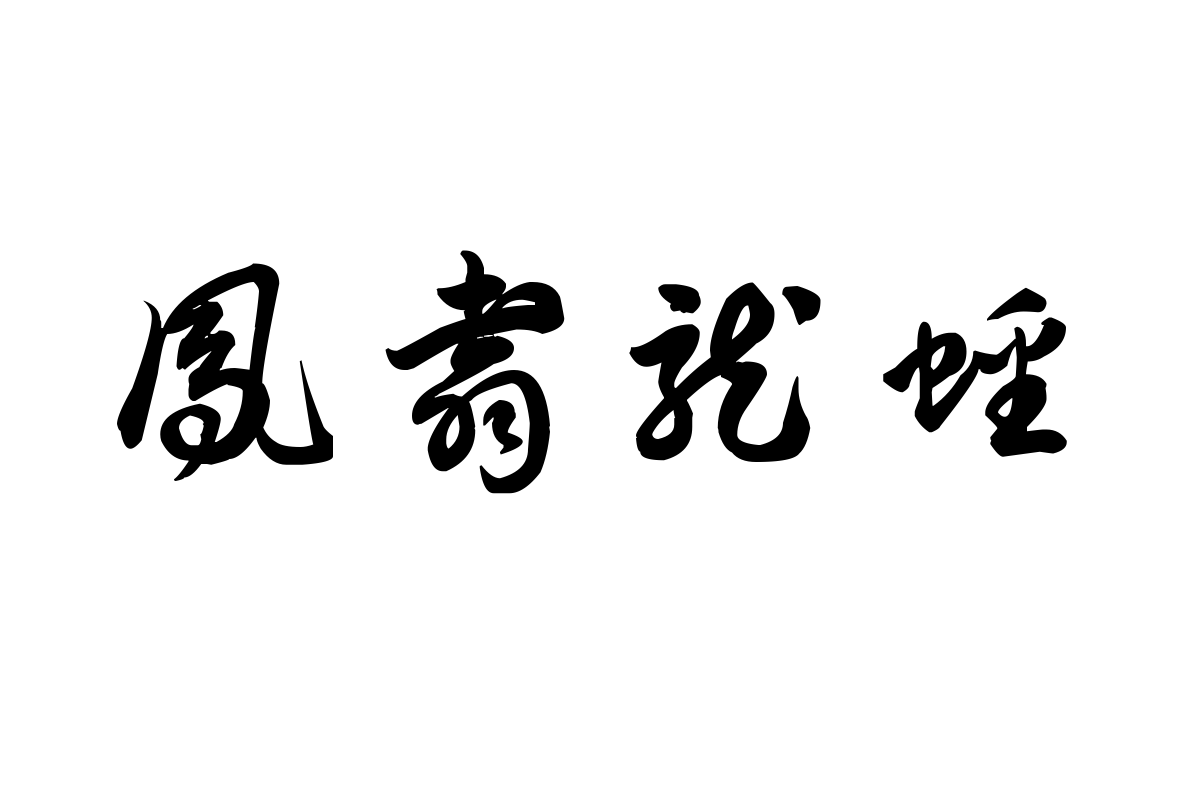
汉呈王天喜草书是一种独特的书法风格,以其流畅、自然、富有表现力的特点而著称。这种字体的特点是线条粗犷有力,笔触饱满,给人一种强烈的视觉冲击力。
在结构上,汉呈王天喜草书注重整体的平衡和协调,每个字的笔画都力求达到完美的对称和和谐。同时,这种字体也强调了空间感和立体感,使得整个作品显得更加生动和有趣。
除了流畅的线条和丰富的表现力外,汉呈王天喜草书还具有一定的艺术性和装饰性。许多书法家在创作时会加入一些象征性的元素,如云纹、波浪等,以增加作品的美感和深度。
总的来说,汉呈王天喜草书是一种充满个性和创造力的书法风格,它不仅展示了书法家高超的技艺,也反映了他们对传统文化的深刻理解和独特见解。